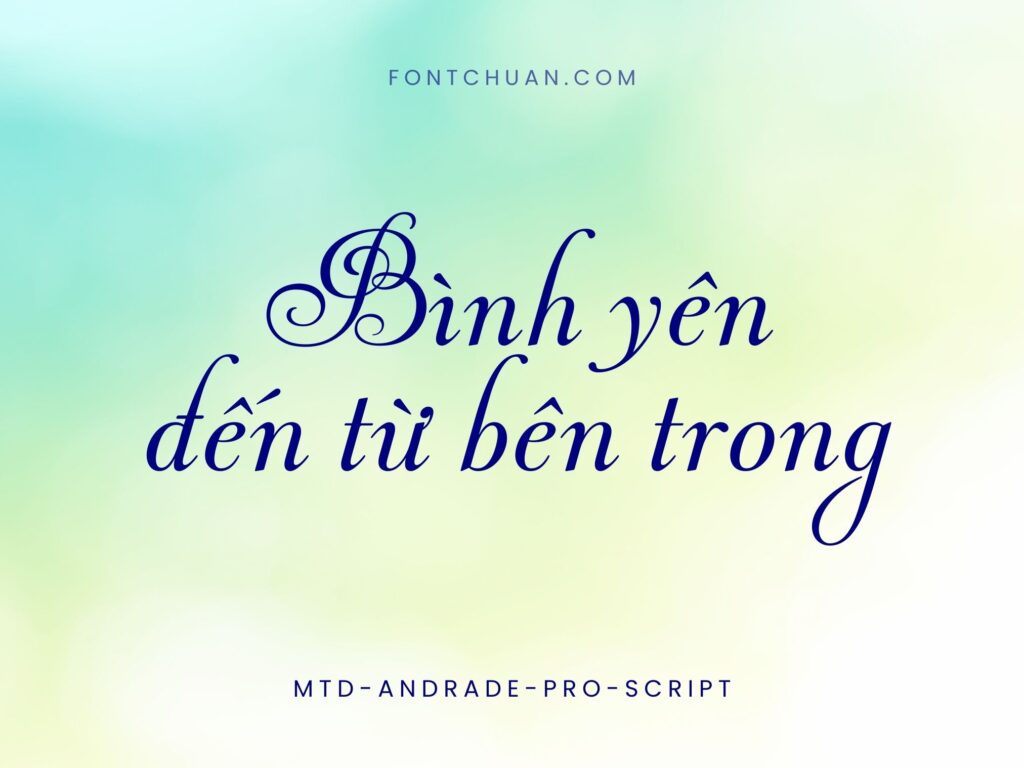
Font Andrade Pro Script là một kiểu chữ serif thanh lịch, được thiết kế bởi DSType Foundry. Với các đường nét tinh tế và phong cách cổ điển, Andrade Pro Script mang lại sự sang trọng và chuyên nghiệp cho các thiết kế.
Phiên bản Andrade Pro Script đã được Việt hóa bởi Mộc Hạ, hỗ trợ đầy đủ tiếng Việt cùng hơn 64 ngôn ngữ khác như Anh, Pháp, Tây Ban Nha, Đức, Ý và Bồ Đào Nha, mở rộng khả năng ứng dụng trong thiết kế đa ngôn ngữ. Font này đã được thành viên Font Chuẩn sưu tầm và chia sẻ, đáp ứng nhu cầu của cộng đồng thiết kế. Với thiết kế bao gồm các ký tự serif mềm mại và ligatures độc đáo, Andrade Pro Script phù hợp cho các ứng dụng như thiết kế logo, tiêu đề, bao bì sản phẩm và các ấn phẩm quảng cáo. Các ngành nghề như quảng cáo, giáo dục, công nghệ và ẩm thực có thể tận dụng font này để tạo ra thiết kế ấn tượng và thu hút.